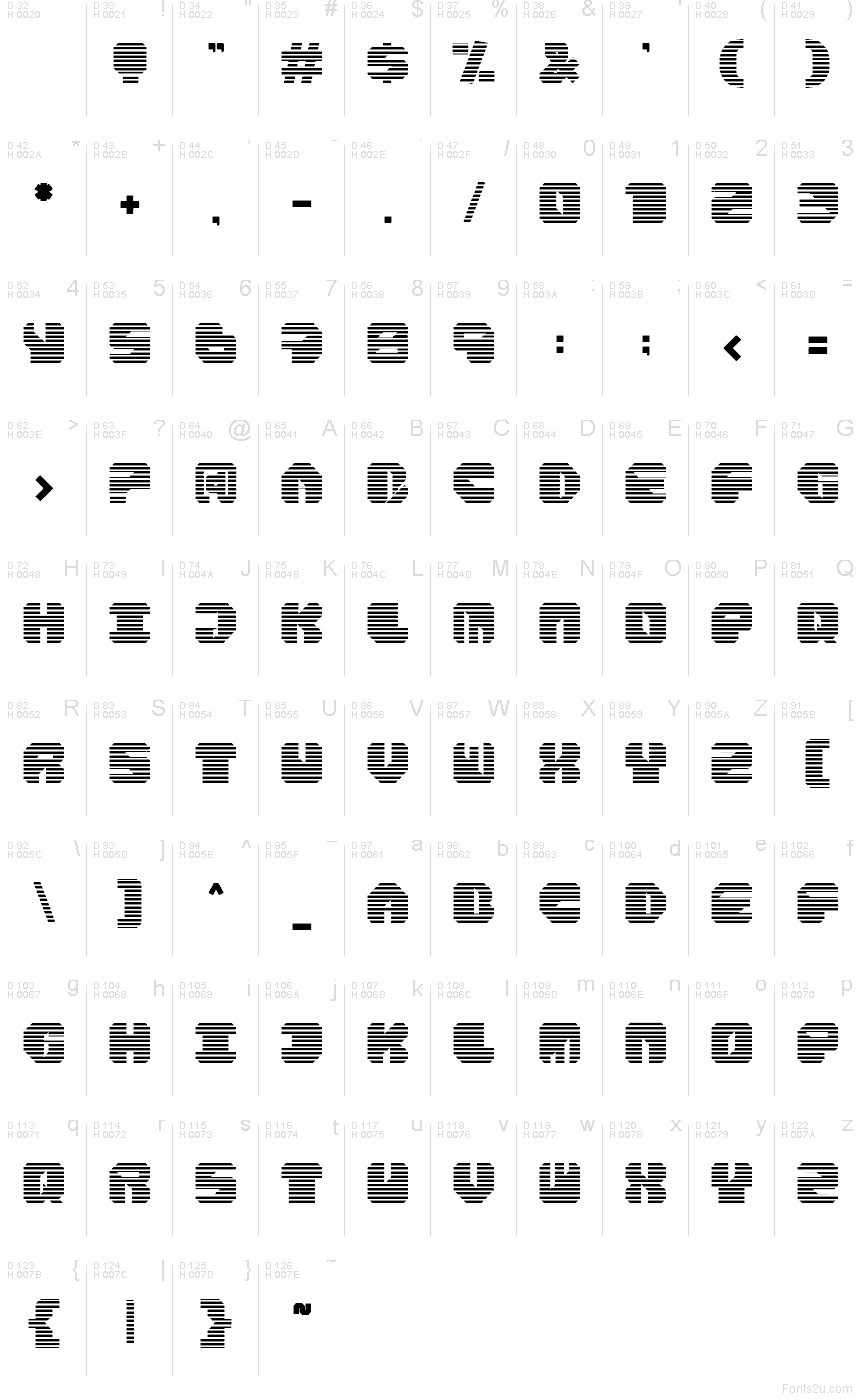
Space Sparkle Seven od Putracetol Studio je bezplatné display písmo s vesmírnou estetikou, definované hustým horizontálním žíháním, které z každého písmene tvoří graficky výrazný celek. Tento opakující se vzor dodává designu texturu „scanline“, zatímco zaoblené oblouky a ostré řezy ukotvují celkovou siluetu pevně ve světě sci-fi.
Font skvěle vynikne v názvech her, nadpisech plakátů, streamovací grafice, obalech alb či technologickém brandingu, kde tato pruhovaná konstrukce nabízí mnohem větší vizuální náboj než běžná písma. Hodí se také pro letáky na akce nebo logotypy, zejména pokud hledáte retro-digitální vzhled namísto neutrálního futuristického písma.
Space Sparkle Seven